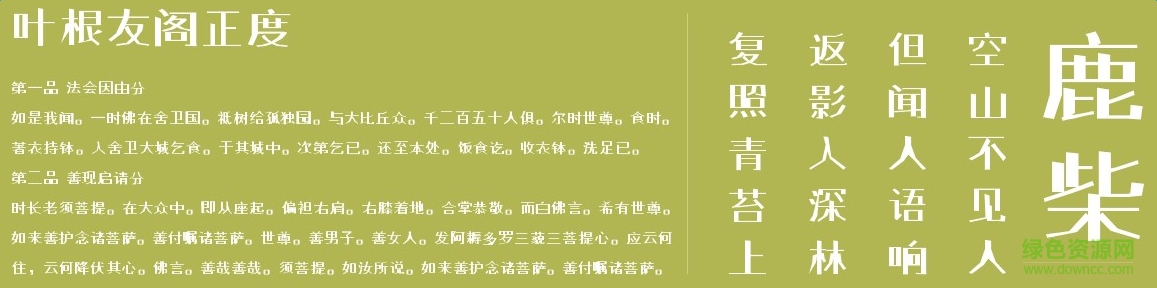
葉根友閣正度字體是一款由知名書法家葉根友創(chuàng)造的字體,比劃圓潤,適用于廣告、藝術(shù)設(shè)計(jì),海報(bào)設(shè)計(jì)等方面,有需要的朋友們不要錯(cuò)過了。歡迎大家來綠色資源網(wǎng)踴躍下載哦!
葉根友閣正度字體,一款經(jīng)典的細(xì)體風(fēng)格的字體,所有葉根友系列字體中筆畫最細(xì)的字體,適合內(nèi)文排版,手機(jī)系統(tǒng),內(nèi)嵌程序等應(yīng)用。
葉根友閣正度字體,用途廣泛,是葉根友先生的印刷字體,字體非常方正有度,仿佛有一根尺子在量身定做,看起來很舒心。各位字體收藏者可以來看看。